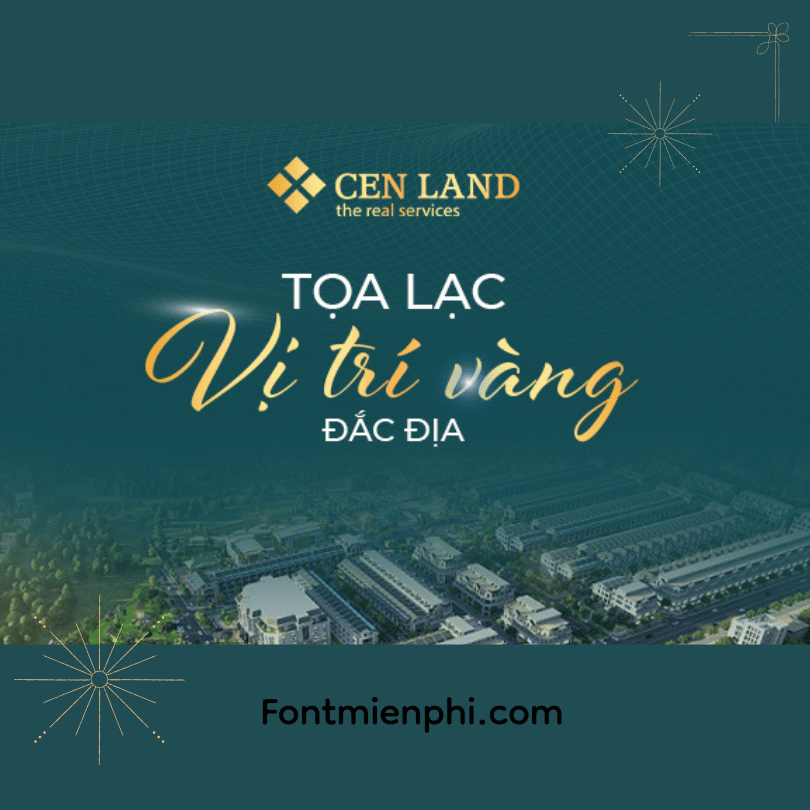
Font combo thiết kế bất động sản 2 , Sẳn hiệu ứng gradient trong file Ps
Font Combo Thiết Kế Bất Động Sản 2 – Bộ Font Chuyên Nghiệp Kèm Hiệu Ứng Gradient
Đặc điểm nổi bật:
• Bộ font combo gồm 2-3 font chữ Việt hóa đẹp, phối hợp hoàn hảo cho thiết kế bất động sản
• Font chữ sắc nét, chuyên nghiệp, phù hợp in ấn catalogue, banner, standee
• Hỗ trợ đầy đủ Tiếng Việt, dùng ngay không cần chỉnh sửa
Ứng dụng:
✔ Thiết kế banner dự án bất động sản
✔ Làm profile công ty, brochure giới thiệu dự án
✔ Thiết kế standee, billboard quảng cáo
✔ Làm hình ảnh truyền thông social media